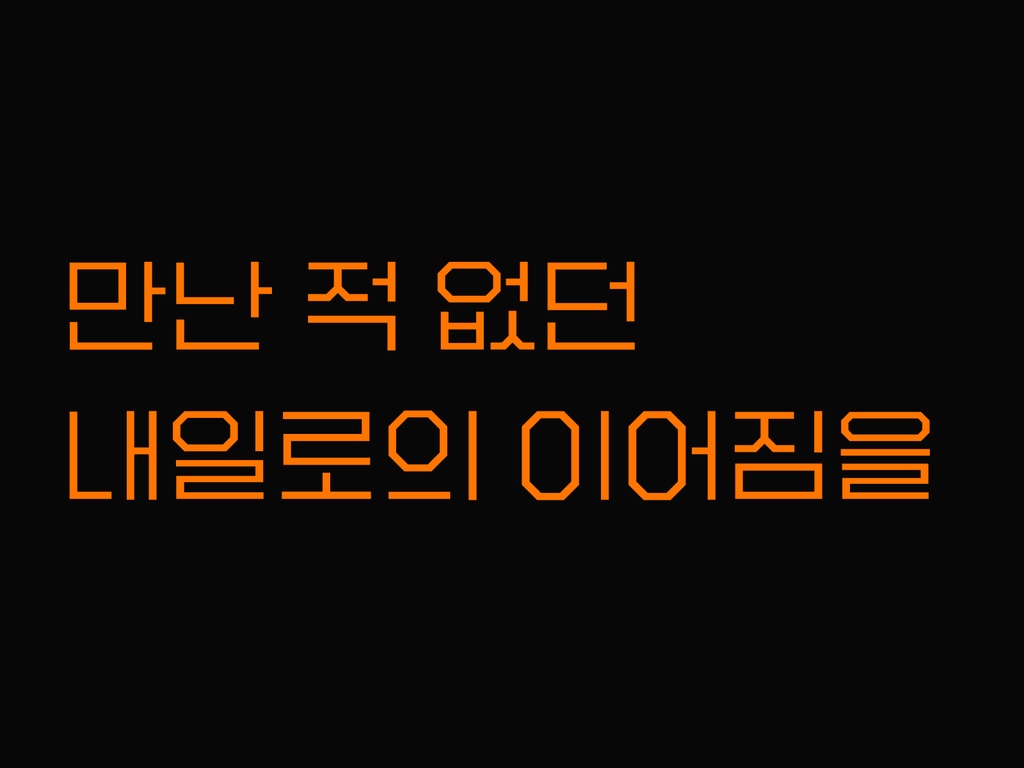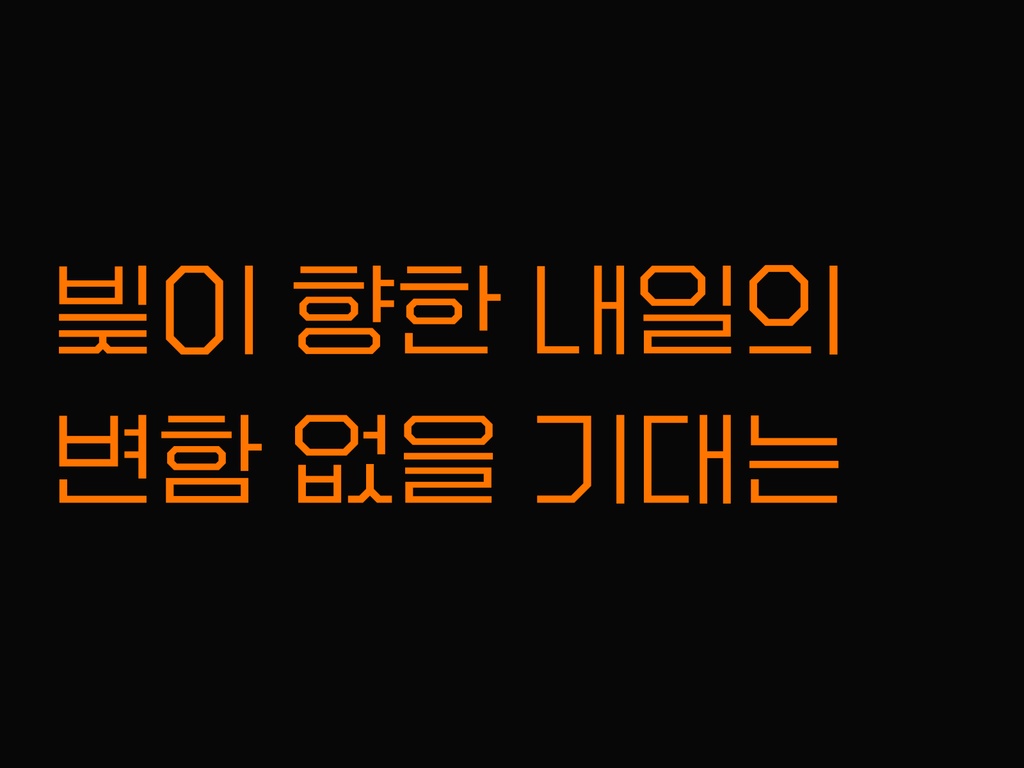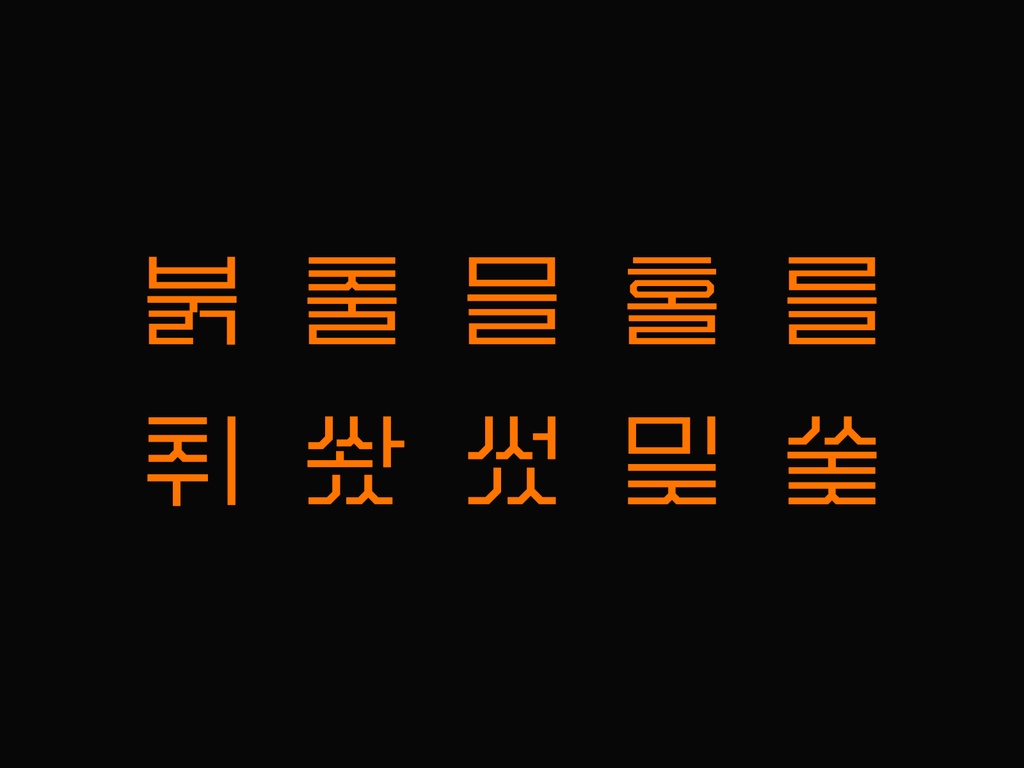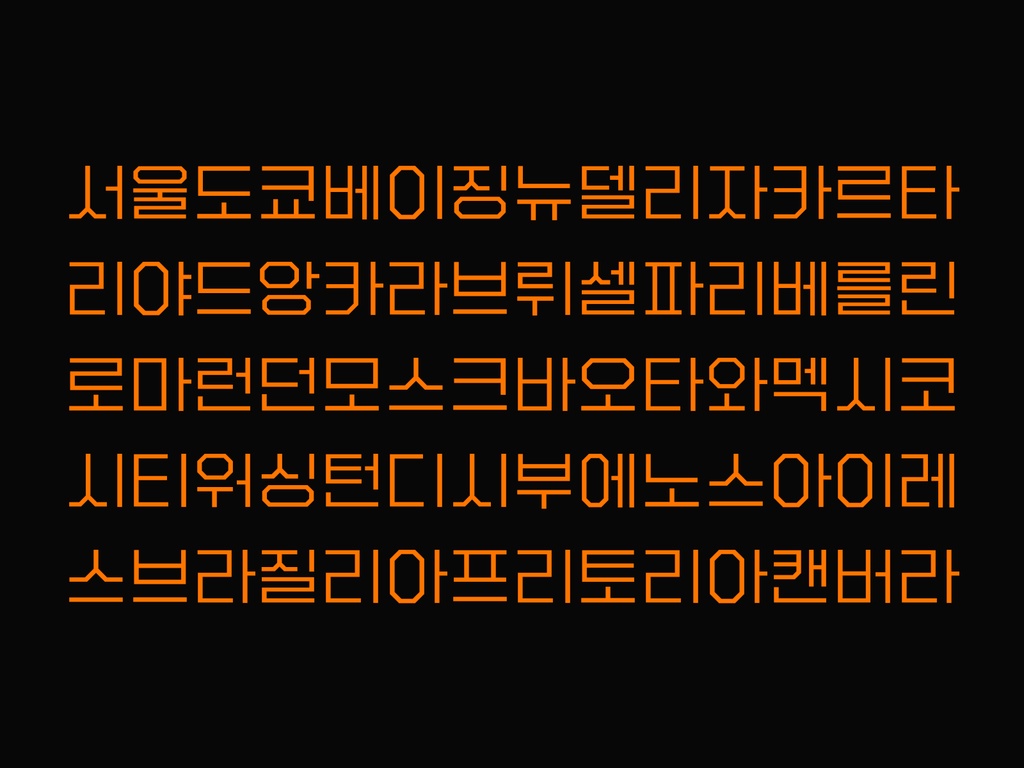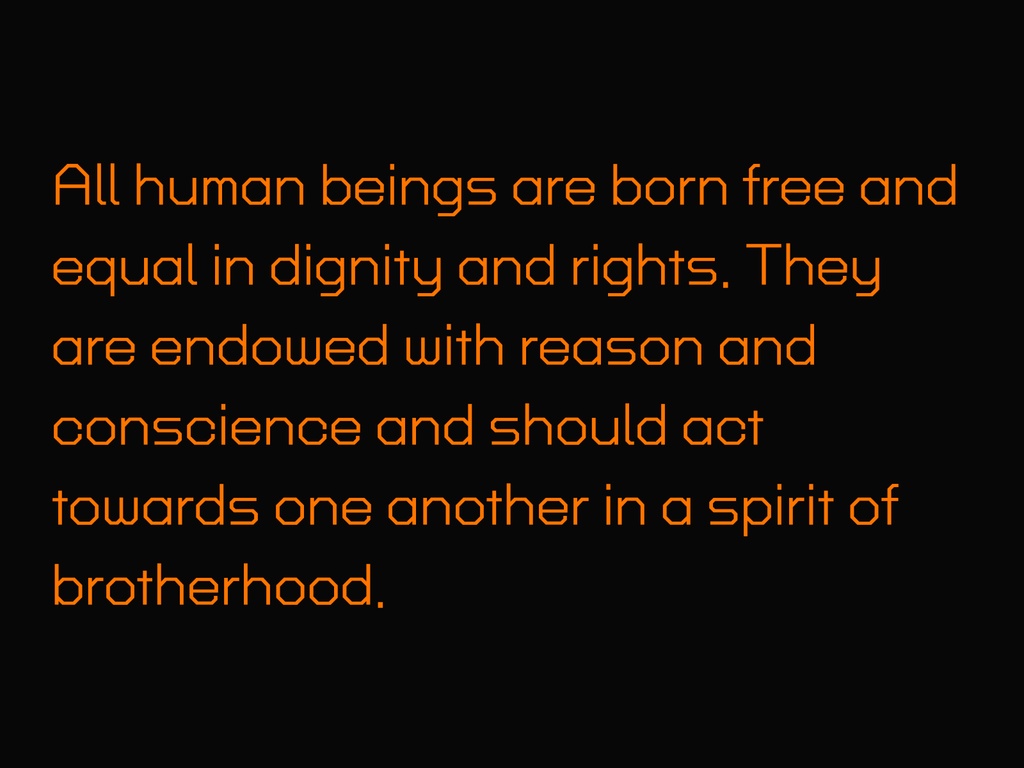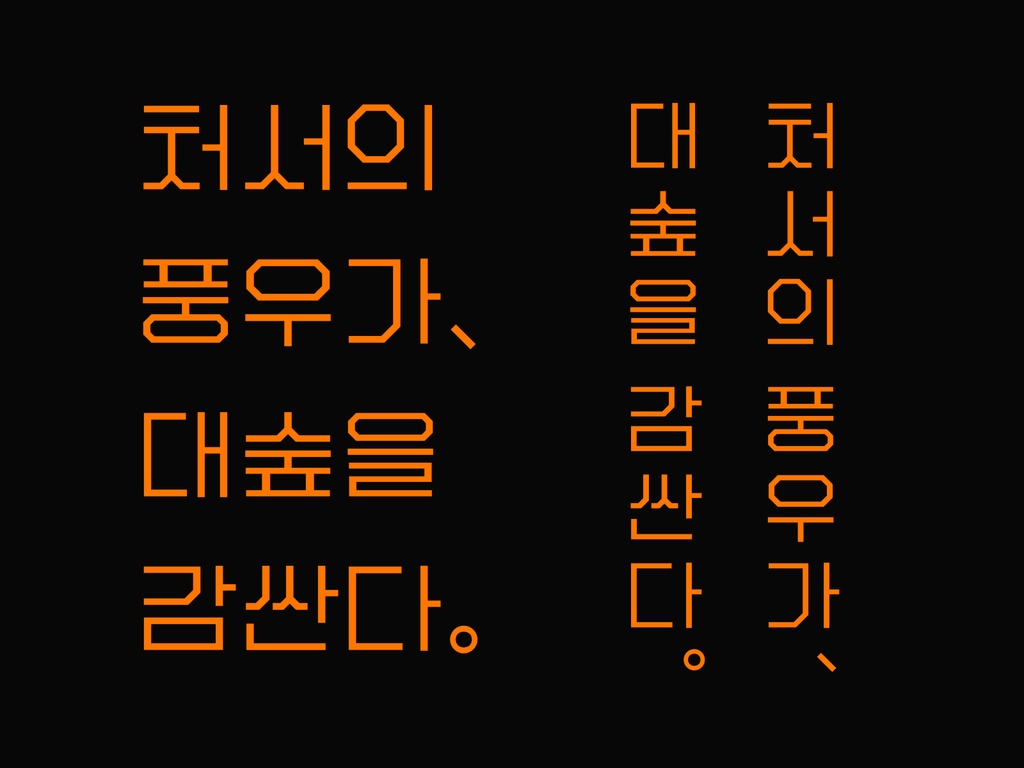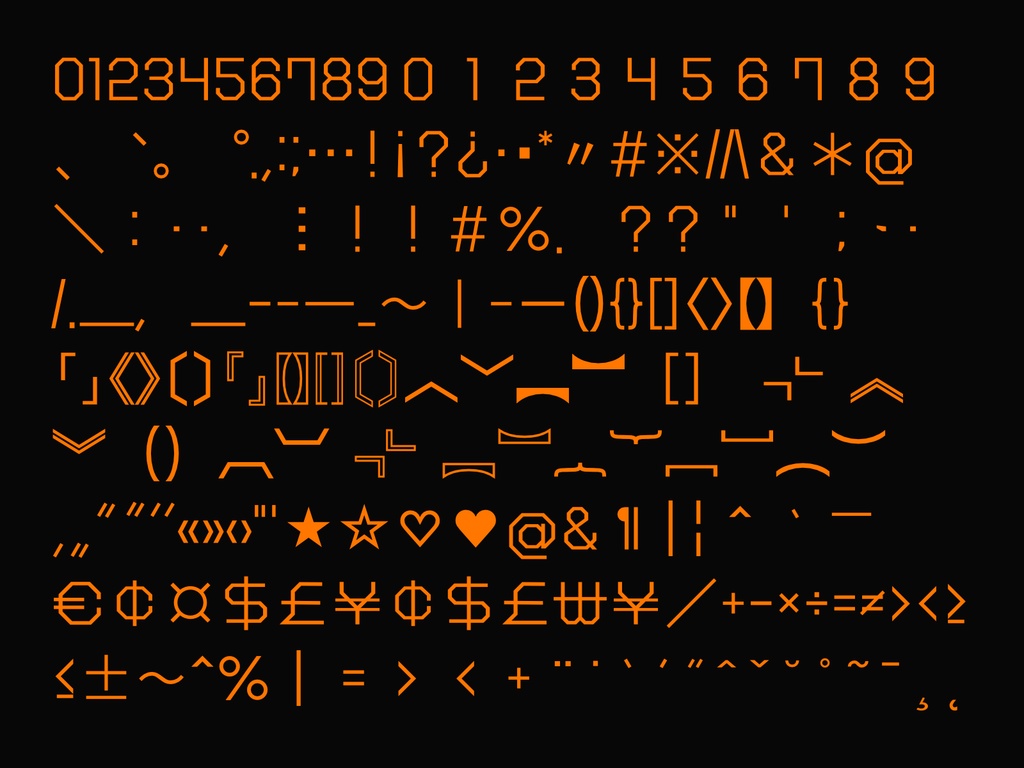
「분기선」은 직선적 형태가 강조되는 제목용 한글 폰트입니다. 정방형에 채워진 올곧은 선들, 하나의 폰트로 만날 수 있습니다. 「분기선」의 모습은 대각선 획이 있는 자음에서 보다 두드러집니다. 획의 곡선은 단순화되어 곧은 형태로 묘사되고, 겹글자에서는 획의 일부가 생략되며 특색을 더합니다. ‘ㅊ’의 덧점은 선형으로 자음 폭을 완전하게 차지하는 동시에 과감한 내부 배치로 인상적인 모습을 보여줍니다. 「분기선」은 한글 2,780자 외에도 로마자 52자 및 확장 로마자, 숫자와 구두점을 포함하여 Adobe-KR-4 및 세로쓰기에 함께 대응하는 특수문자의 표시가 가능합니다. 정방형의 틀에 맞춰진 「분기선」으로 정렬된 한글의 새로운 모습을 만날 수 있습니다. 【폰트 소프트웨어 사용권 계약】: https://rebrand.ly/81c898 • 구성: 한글 2,780자, 로마자 52자, 숫자 및 Adobe-KR-4와 세로쓰기에 대응하는 기타 특수문자 147자 이상의 구현이 가능한 폰트 파일(기본 OTF, 웹폰트는 WOFF2와 WOFF로 제공) • 이용 범위: • 【라이선스 에센셜】: 라이선스 스튜디오에서 규정되지 않는 범위에서의 다음 사용처: 상업적 이용을 포함한 지류 및 전자매체 인쇄·출판·출력물 및 문서, SNS 게시물 이미지, 그림, 만화, 1인 독자 제작-배포 영상 및 해당 영상 섬네일, 개인 비영리 표시물(손팻말·깃발·현수막·디지털 디스플레이 등) (1인 1라이선스, 문서 임베딩: 보기 및 프린트 가능) • 【라이선스 스튜디오】: 상업적 이용을 포함한 지류 및 전자매체 인쇄·출판·출력물 및 문서, 디지털 이미지, 그림, 만화, 영상·영상 섬네일, 광고, 상징(로고·아이덴티티·아이콘·프로필 미디어), 명함, 표시물(손팻말·깃발·현수막·디지털 디스플레이·간판·광고판·안내판·차림표·배너 등), 디지털 스탬프·스티커·이모티콘, 배경화면, UI 이미지, 소프트웨어 내장 이미지, 3D 데이터, 도안·도면, 패키지, 스티커, 랩핑, 실물 제품 적용 (1인 1라이선스, 문서 임베딩: 보기 및 프린트 가능) • 【라이선스 웹폰트】: 웹폰트 적용: Gumroad 판매 페이지 참조 • 【라이선스 임베딩】: 소프트웨어 및 제품상 임베딩: Gumroad 판매 페이지 참조 • 어떤 라이선스가 가장 좋은 선택인가요? 라이선스 에센셜은 보다 합리적인 가격으로 폰트를 사용할 수 있는 선택입니다. 일반적인 출판물과 문서, SNS 업로드용 이미지, 직접 만들어 올리는 영상이나 직접 만들어 사용하는 비영리적 표시물에 폰트를 사용하고자 한다면 라이선스 에센셜만으로도 충분합니다. 하지만 만약 명함이나 로고, 프로필 사진과 헤더 등에 폰트를 사용하여 자신만의 정체성을 나타내고자 하거나 각종 실물 제품 및 디지털 상품, 상업적 이용을 포함한 간판과 현수막 등의 표시물, 광고, 여러 사람이 참여하는 영상 제작 등 다양한 사용처에 폰트를 사용하고자 한다면 라이선스 스튜디오가 이상적입니다. 사이트에 웹폰트를 적용하고자 한다면 웹폰트, 소프트웨어 및 제품상 임베딩을 원한다면 임베딩을 선택해야 합니다. 구매 과정상 구매 후 업그레이드는 공식 지원되지 않습니다. • 라이선스를 공유할 수 있나요? 기본적인 라이선스는 1인 1라이선스입니다. 다만 웹폰트와 임베딩 라이선스의 경우 해당 사용처에 귀속됩니다. • 구매 과정에서 별도의 수수료가 있나요? BOOTH는 사전 책정된 엔화, Gumroad는 원화에 상응하는 환산 달러를 기준으로 결제됩니다. BOOTH 및 Gumroad의 경우 특성상 사용 결제 수단에 따라 소정의 해외 결제 수수료가 존재할 수 있는 한편, 결제 수단에 따라서는 해외 결제 혜택을 받을 수도 있기 때문에 사용 가능한 결제 수단의 혜택을 고려하는 것이 좋습니다. 포스타입의 경우 결제를 위한 충전 금액이 지정되어 있기 때문에 충전 금액과 사용 금액에 따라서는 잔여 충전액이 발생할 수 있습니다. 또한 브라우저를 통해 포인트를 충전할 시 부과되지 않으나, 모바일 앱을 통한 충전 시 결제 수수료가 추가됩니다. Gumroad의 경우 세무 처리 과정상 사업자번호를 입력하지 않는 개인 구매자는 결제 금액에 세액이 함께 부과될 수 있습니다. 본 상품은 라이선스 에센셜 상품입니다. 다른 라이선스는 다음에서 구매할 수 있으며, 다중 구매 및 라이선스 웹폰트·임베딩은 Gumroad를 이용하여 주십시오. • BOOTH: https://yimu-type.booth.pm • Gumroad: https://gum.co/u/rxjgqtfi BOOTH와 Gumroad에서는 폰트를 선물할 수 있습니다. 선물을 원할 경우 BOOTH에서는 상품 화면에서 「기프트 보내기」를, Gumroad에서는 결제 화면에서 Give as a gift를 선택하십시오. SNS를 구독하실 경우 업데이트 등 변경 사항을 쉽게 전달받으실 수 있습니다. • 트위터: @yimu_type - https://rebrand.ly/3e85e1 • 인스타그램: @yimu_type - https://rebrand.ly/04a818 https://yimu-type.tumblr.com 오류 제보·의견 제출: https://rebrand.ly/6b80a9